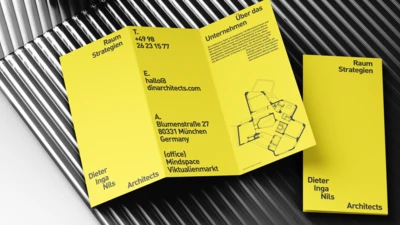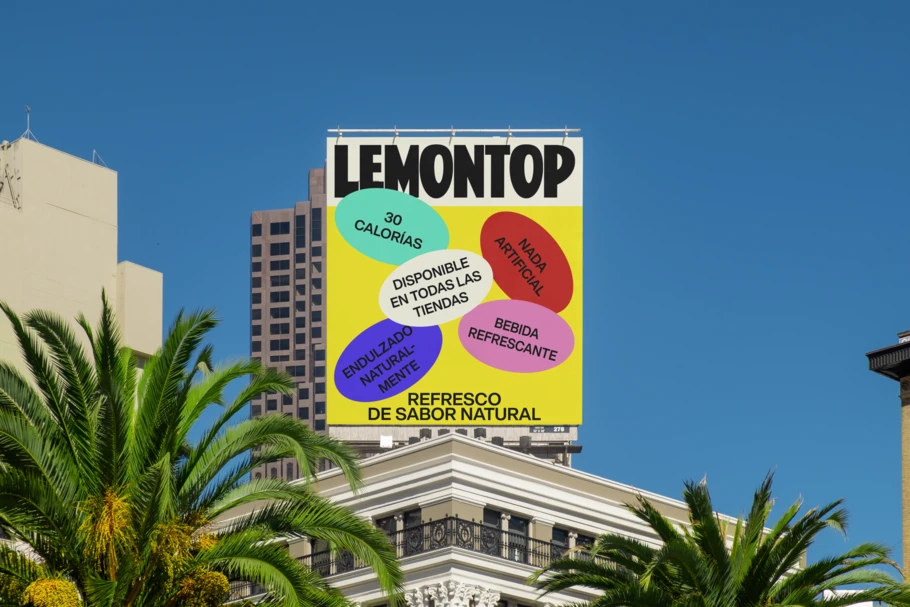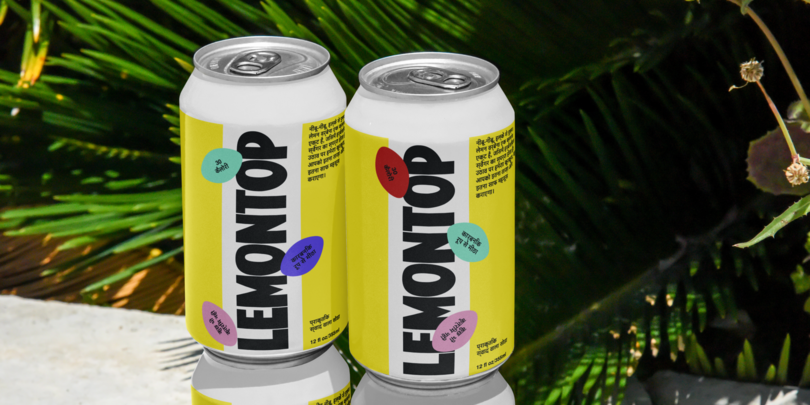
Guía para crear una identidad de marca coherente, eficaz y única.
En palabras de Charles Nix, director creativo de Monotype: «La identidad de marca es algo vivo; no hay ninguna marca que sea estática». Dado que las marcas evolucionan continuamente, se necesitan pilares que las mantengan unidas.
La tipografía es uno de esos pilares. Aunque son los equipos de diseño los que se devanan los sesos con el ojo medio y la forma de la «g» de un tipo de letra concreta, todas las personas que conforman las organizaciones tienen cierta responsabilidad a la hora de asegurar la coherencia de marca.
La coherencia debe ser el pan de cada día.
Sabemos que las marcas son algo poderoso. Sirven para transmitir confianza, definir la identidad, crear una ética sólida y lograr que los clientes regresen. Hacer un uso coherente de la tipografía ayuda a que todo el mundo esté en sintonía y reme en la misma dirección. Al definir y mantener una tipografía congruente, estás afirmando que los valores de tu marca importan, que crees en ellos y que los llevas por bandera. La forma en que tu equipo se comunica internamente de manera verbal y visual son un fiel reflejo de ello.
Para que tus clientes sepan quién eres, confíen en ti, quieran hacer negocios contigo y estén dispuestos a darte dinero y a ayudarte a triunfar, tu marca debe conocerse a sí misma y reflejar esa identidad en todo momento. Tener una tipografía coherente y buena no es ningún lujo, no es el menú de un restaurante exclusivo. Es el pan de cada día. El mínimo. Una necesidad empresarial.
Cómo definir y mantener la coherencia.
Puede ser difícil predecir el recorrido de una marca a lo largo de los años. Piensa en las empresas que existían antes de que llegaran Internet y las aplicaciones. Las fuentes web eran inimaginables. Las marcas del mundo de la Web2 tendrán que adaptarse a los cambios de la Web3, el metaverso y lo que sea que nos depare el futuro. Dicho esto, ¿qué pueden hacer las organizaciones para asegurarse de que sus tipos de letras y su identidad de marca sean coherentes? Veámoslo.
Ten claras tus fuentes de texto y display.
Tanto si estás diseñando productos promocionales como si estás haciendo un encabezado o una presentación interna, es fundamental que sepas desde el principio cuáles son las fuentes primarias y secundarias de la marca. Aunque no hay un mínimo de tipos de letras que pueda elegir una marca (y usar una única fuente requiere un alto nivel de disciplina), es importante tener claras al menos las fuentes de texto y las posibles fuentes display. Además, es posible que debas recurrir a tu maletín de profesional del diseño para sacar algo mágico, como una nueva fuente display para una ocasión especial. Disponer de un método general para saber qué recursos corresponden a cada marca es el primer paso para triunfar.
Apuesta por la sencillez: serif o sans serif.
Aquí va una regla de oro del mundo de la identidad de marca, además de la jerarquía de la tipografía: si el sistema es tan complejo que ni siquiera quienes lo han creado pueden seguir el hilo, olvídate de que puedan hacerlo el resto de las empresas asociadas a la marca. Con Monotype Fonts como plataforma de gestión, las personas encargadas de la administración tienen una visibilidad general de las fuentes de la organización y solo otorgan acceso a aquellas que la plantilla debe usar.
Pon a todo el mundo en sintonía.
La voz de una marca se expresa a través de la tipografía. Todo el personal de las marcas debe tenerlo claro y aceptarlo, tanto si su trabajo está relacionado directamente con el diseño como si no. Tener una plataforma o sistema que integre de forma sencilla las fuentes de marca en un programa de diseño facilita esta tarea. Con Monotype Fonts, solo hay que pulsar el botón «Sincronizar». Tener claro cuál es el propósito de la empresa y por qué se elige cada fuente ayuda a crear una marca sólida, tanto a nivel interno como desde un punto de vista psicológico.
Haz auditorías de marca con frecuencia.
La identidad de marca es algo vivo. Por ello, es recomendable hacer auditorías de marca o evaluaciones internas de forma regular y recurrir a empresas externas. Las evaluaciones deben llevarse a cabo desde un punto de vista general y minucioso. Se debe tener en cuenta la coherencia, la voz de marca y la relevancia del tamaño, el contraste del color y la legibilidad, entre otros factores. El servicio de evaluación de la tipografía de marca de Monotype puede proporcionarte esta información para lograr que todo esté en sintonía y sacar a la luz cualquier problema del sistema.
La comunicación es lo más importante.
Aunque los valores, el nombre, el logotipo, la misión y otros elementos cambien, constituyen la esencia de la marca, y la tipografía es la forma de expresar todos estos elementos. Si hay algún cambio, comunícalo. Si hay algún problema de acceso, arréglalo. Por ejemplo, si usas Monotype Fonts, todos los miembros de los equipos de diseño y digitales deben tener el acceso que necesiten.